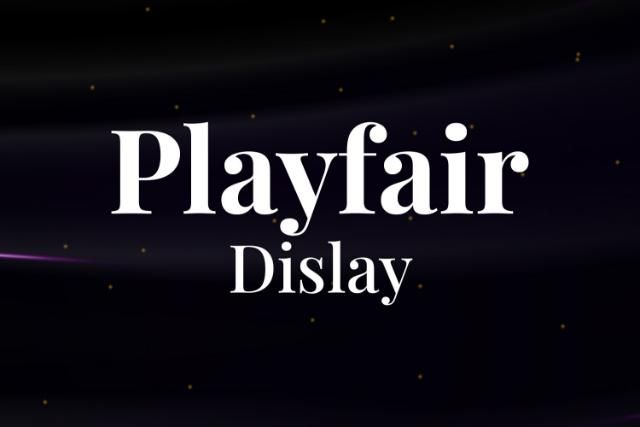
Font chữ có chân (Serif) là dòng phông chữ kinh điển với các đường gạch nhỏ ở đầu hoặc cuối nét chính của ký tự. Trong lĩnh vực kiến trúc và đồ họa, phông chữ này thường gợi nhắc đến sự trang trọng, uy tín và bề dày lịch sử. Việc sử dụng các bộ phông chữ có chân giúp các bản thuyết minh dự án, hồ sơ năng lực hay bảng hiệu khu nghỉ dưỡng toát lên vẻ thanh lịch và đẳng cấp.
Đặc điểm thẩm mỹ của các dòng font chữ có chân trong thiết kế
Nét đặc trưng của dòng phông này nằm ở khả năng dẫn dắt thị giác nhờ hệ thống chân chữ tinh tế. Cấu trúc này không chỉ mang lại vẻ đẹp cổ điển mà còn giúp mắt người đọc dễ dàng theo dõi các dòng văn bản dài trên mặt giấy in. Các mẫu font chữ có chân đẹp hiện nay thường được chia thành nhiều nhánh nhỏ như phông chữ có chân mảnh thanh thoát hoặc font chữ có chân vuông mang lại cảm giác vững chãi và chắc chắn như các khối kết cấu công trình.
Phiên bản font chữ có chân sang trọng Việt hóa đã được tinh chỉnh hệ thống dấu thanh sao cho cân đối với trọng lượng của từng ký tự. Điều này đảm bảo các từ ngữ tiếng Việt không bị lỗi hiển thị, duy trì được nhịp điệu sang trọng của bộ gốc. Đây là lựa chọn phù hợp để định hình phong cách cho các dự án kiến trúc nghỉ dưỡng, homestay hay những thương hiệu muốn khẳng định sự chuyên nghiệp và chỉn chu trong từng chi tiết nhỏ nhất.
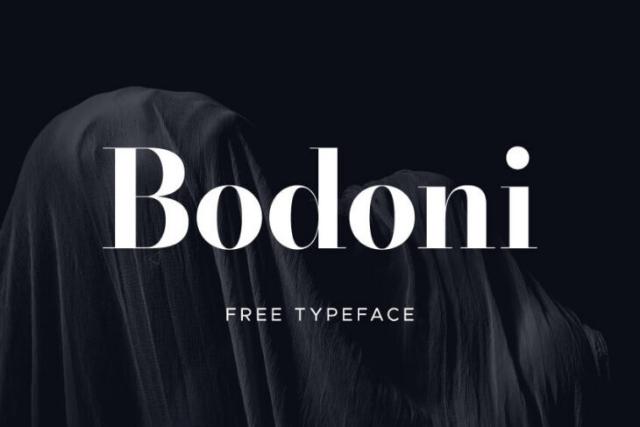
Thông số kỹ thuật và download font chữ có chân Việt hóa trọn bộ
Để hỗ trợ bạn lựa chọn được kiểu chữ phù hợp với tính chất dự án, dưới đây là bảng thông số chi tiết của một số nhóm phông chữ có chân phổ biến hiện nay.
| Nhóm phông tiêu biểu | Đặc tính thiết kế | Ứng dụng phù hợp |
|---|---|---|
| Old Style / Transitional | Độ tương phản vừa phải, dễ đọc | Nội dung thuyết minh, hợp đồng |
| Modern / Didone | Tương phản nét thanh đậm cao | Tiêu đề font chữ có chân sang trọng |
| Slab Serif | Chân chữ dày, vuông vức, khỏe khoắn | Biển tên font chữ có chân đậm |
| Glyphic | Chân chữ nhỏ như nét khắc đá | Logo kiến trúc, số nhà, decor |
Gợi ý lựa chọn: Bạn nên sử dụng các kiểu font chữ có chân đẹp thuộc nhóm Old Style cho các văn bản dài để tối ưu trải nghiệm đọc. Trong khi đó, các dòng font chữ có chân đậm hoặc chân vuông sẽ phát huy hiệu quả thị giác mạnh mẽ khi làm tiêu đề cho các hồ sơ năng lực dự án nhà lắp ghép, tạo cảm giác về một đơn vị thi công vững mạnh.
03 Ứng dụng phông chữ có chân vào thực tế công trình
Nhờ diện mạo trang trọng và khả năng nhận diện cao, bộ phông chữ này mang lại giá trị thực tế lớn trong khâu quảng bá và hoàn thiện các công trình hiện đại:
- Hệ thống nhận diện cho Resort & Boutique Hotel: Những nét chữ của các font chữ có chân đẹp rất ăn ý khi xuất hiện trên chất liệu đồng, inox gương hoặc gỗ sơn mài. Phông chữ này giúp không gian nghỉ dưỡng toát lên vẻ cao cấp, thu hút nhóm khách hàng yêu thích sự tinh tế.
- Hồ sơ năng lực và Portfolio kiến trúc: Sử dụng font chữ có chân sang trọng Việt hóa cho các tiêu đề trang mục giúp thể hiện tư duy thẩm mỹ và sự làm việc bài bản của đơn vị thiết kế, tạo niềm tin vững chắc đối với chủ đầu tư.
- Trang trí không gian nội thất hoài cổ: Bạn có thể dùng phông chữ có chân vuông để cắt chữ nổi hoặc in tranh quote trang trí tại phòng khách, sảnh chờ văn phòng container, tạo điểm nhấn đầy thẩm mỹ và chiều sâu văn hóa.
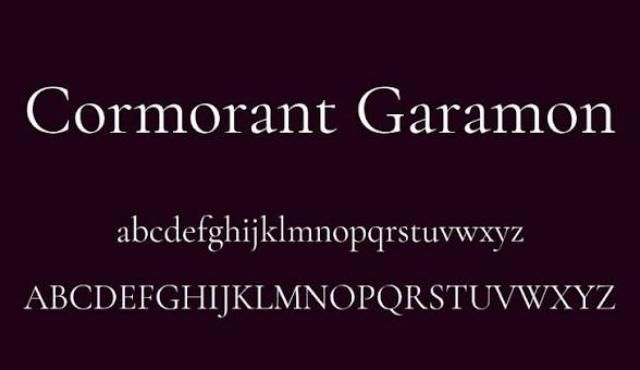
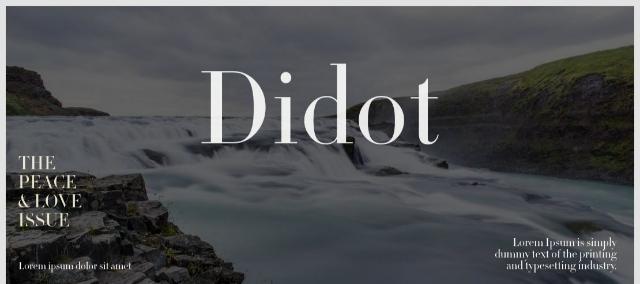
03 Lưu ý bố cục với font chữ có chân đẹp để đạt hiệu quả cao
Để khai thác hiệu quả vẻ đẹp của dòng phông chữ đặc thù này mà không làm rối mắt người xem, người thiết kế nên lưu tâm một số lưu ý kỹ thuật sau:
- Kiểm soát khoảng cách dòng: Do phông có chân có cấu trúc ký tự chi tiết hơn phông không chân, bạn nên nới rộng khoảng cách dòng một chút để các chân chữ không bị chồng lấn, giúp văn bản trở nên minh bạch và dễ đọc hơn.
- Phối hợp cùng phông không chân: Một công thức phổ biến là sử dụng font chữ có chân đậm cho tiêu đề và dùng phông không chân cho phần nội dung chi tiết. Sự tương phản này giúp bố cục hồ sơ báo giá của bạn trông hiện đại và chuyên nghiệp.
- Lựa chọn kích thước hiển thị: Tránh sử dụng các bộ phông có chân quá mảnh ở kích thước nhỏ trên các biển hiệu ngoài trời, vì các nét thanh có thể bị nhòa mờ dưới tác động của ánh sáng và khoảng cách quan sát.